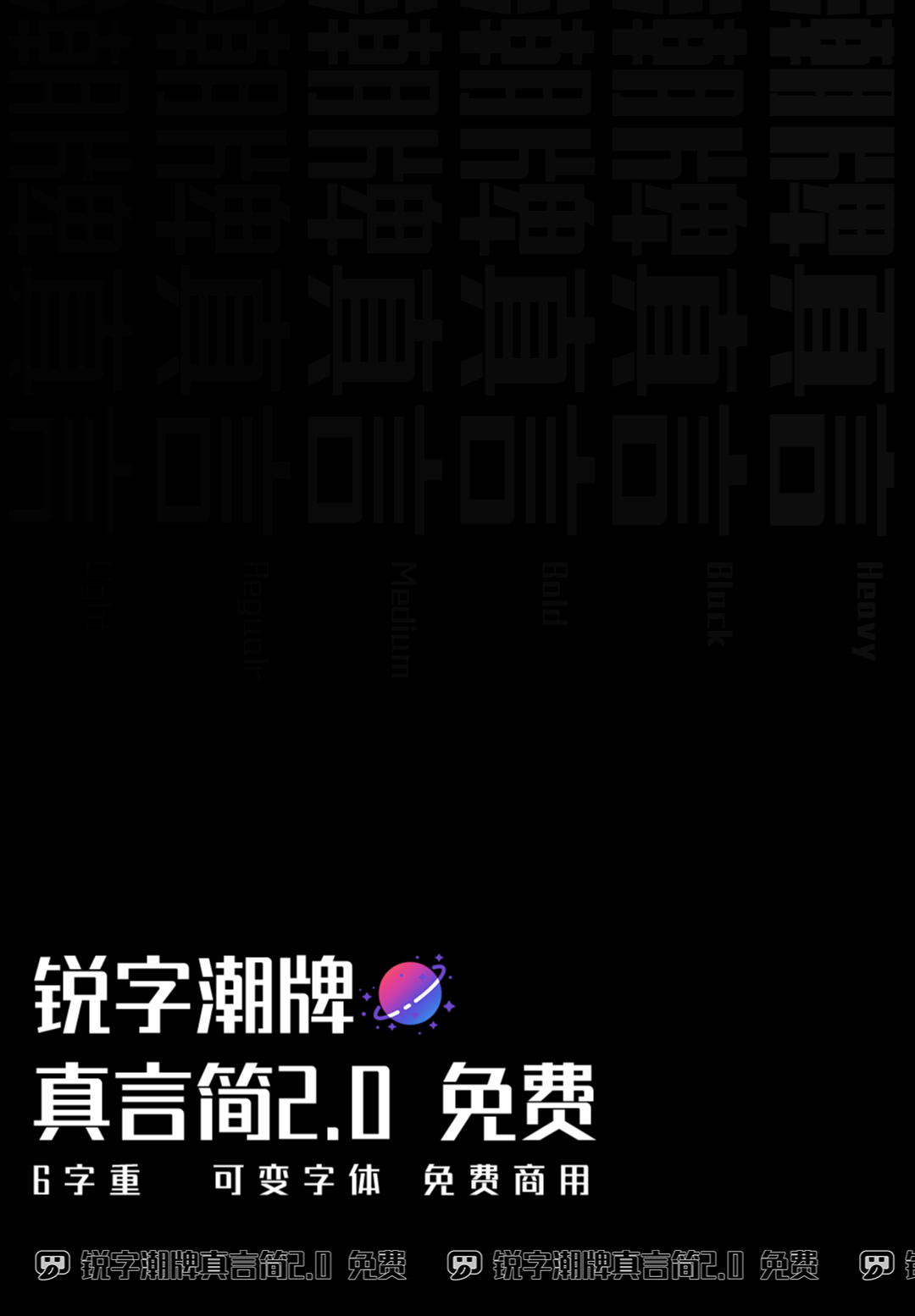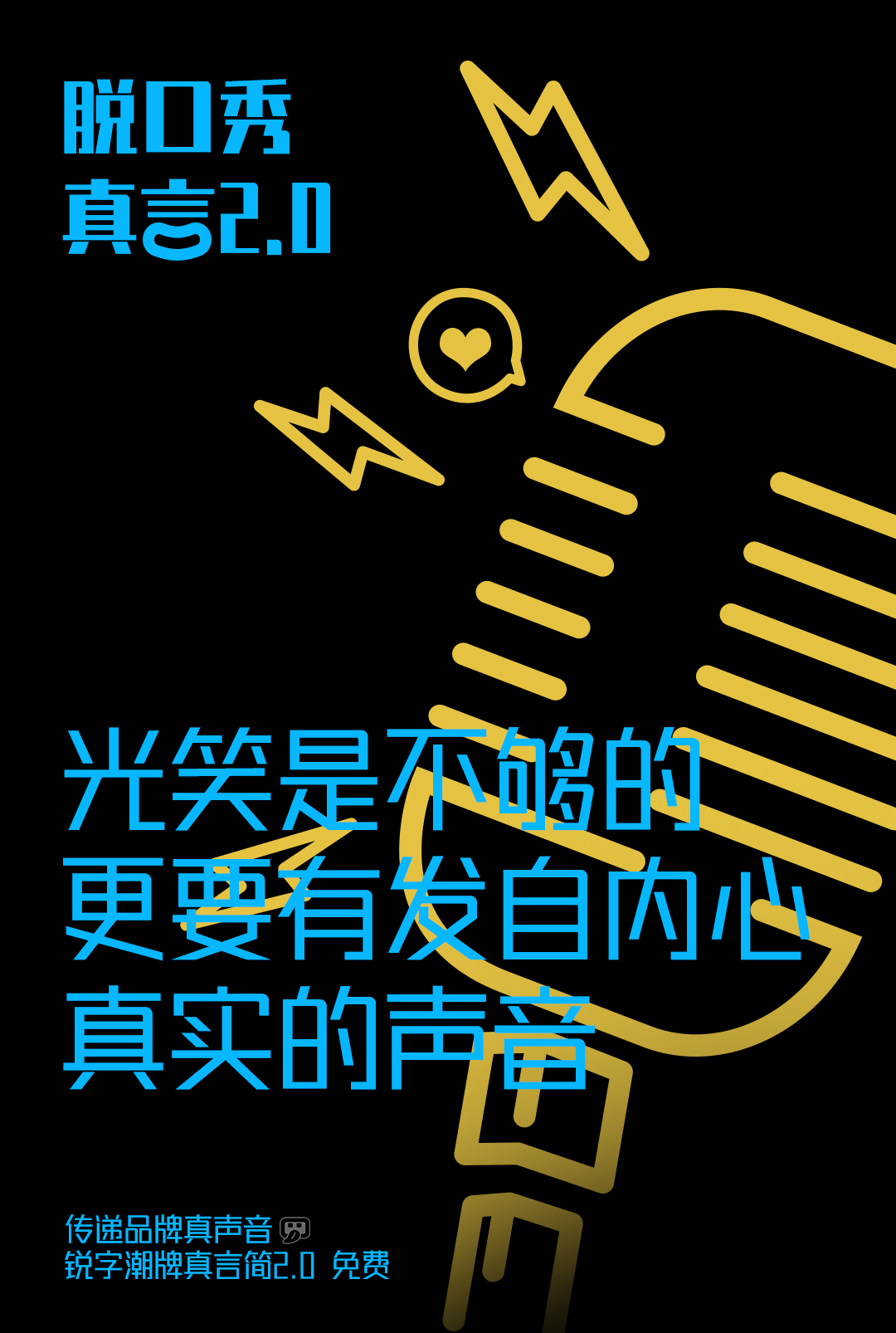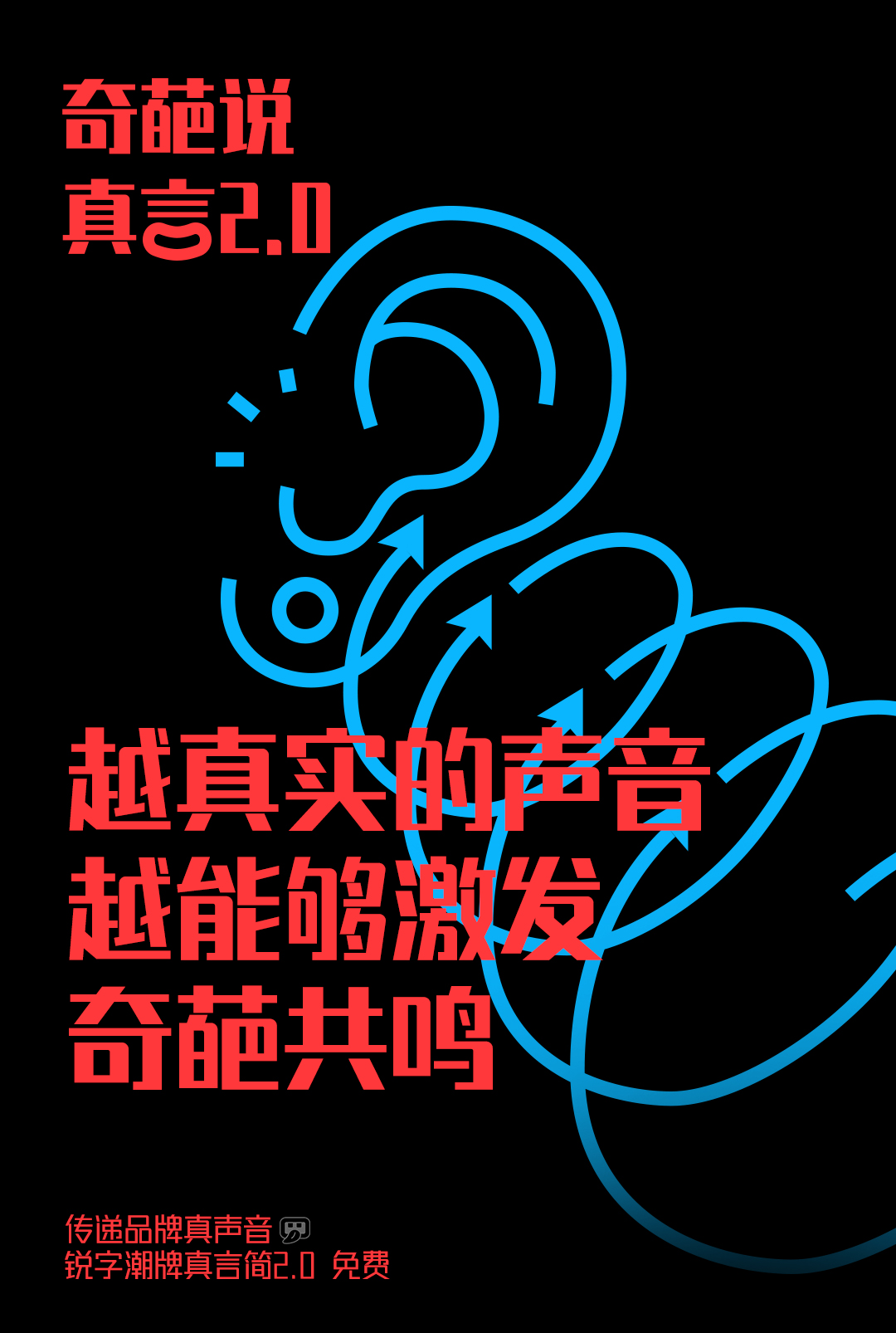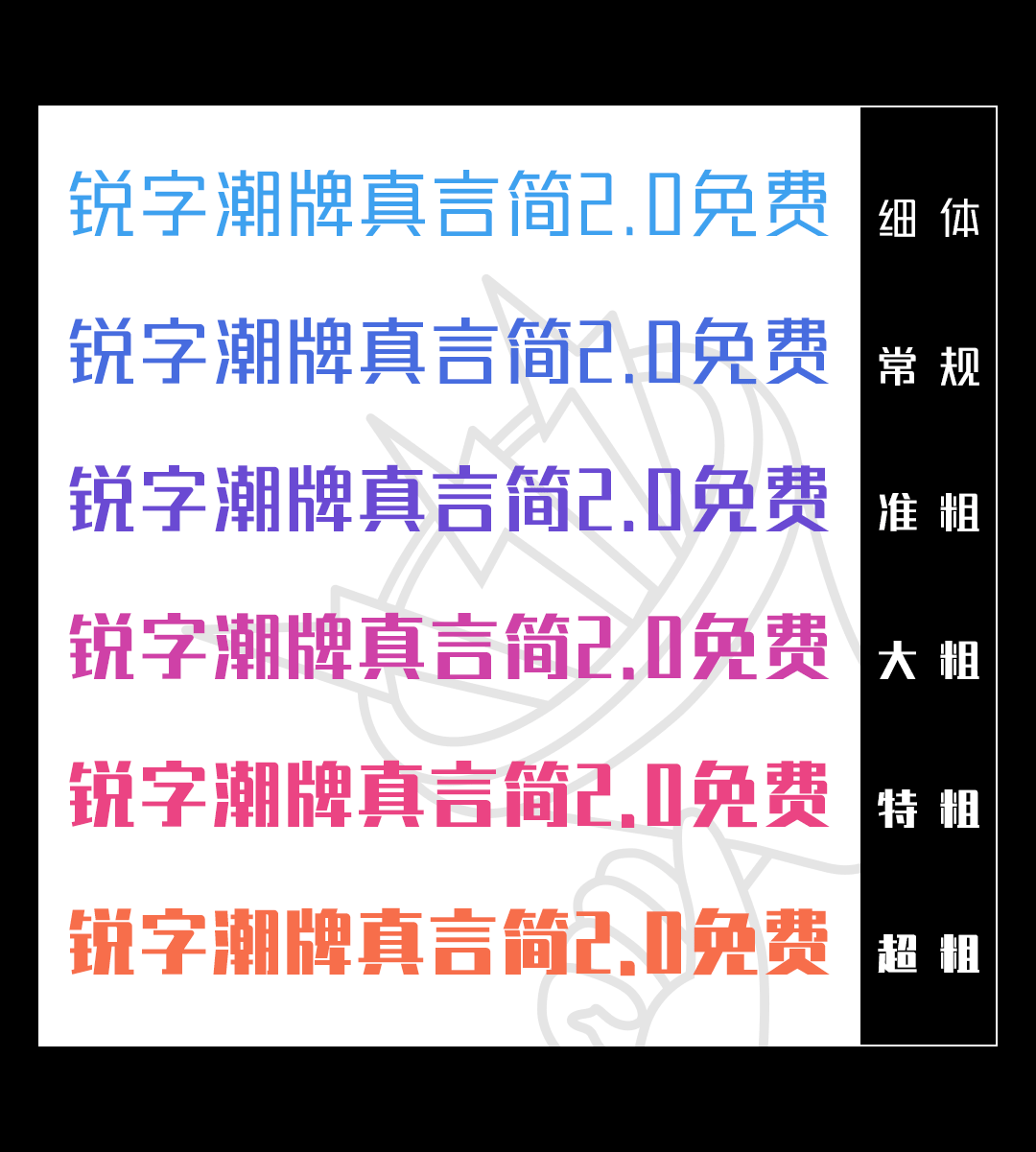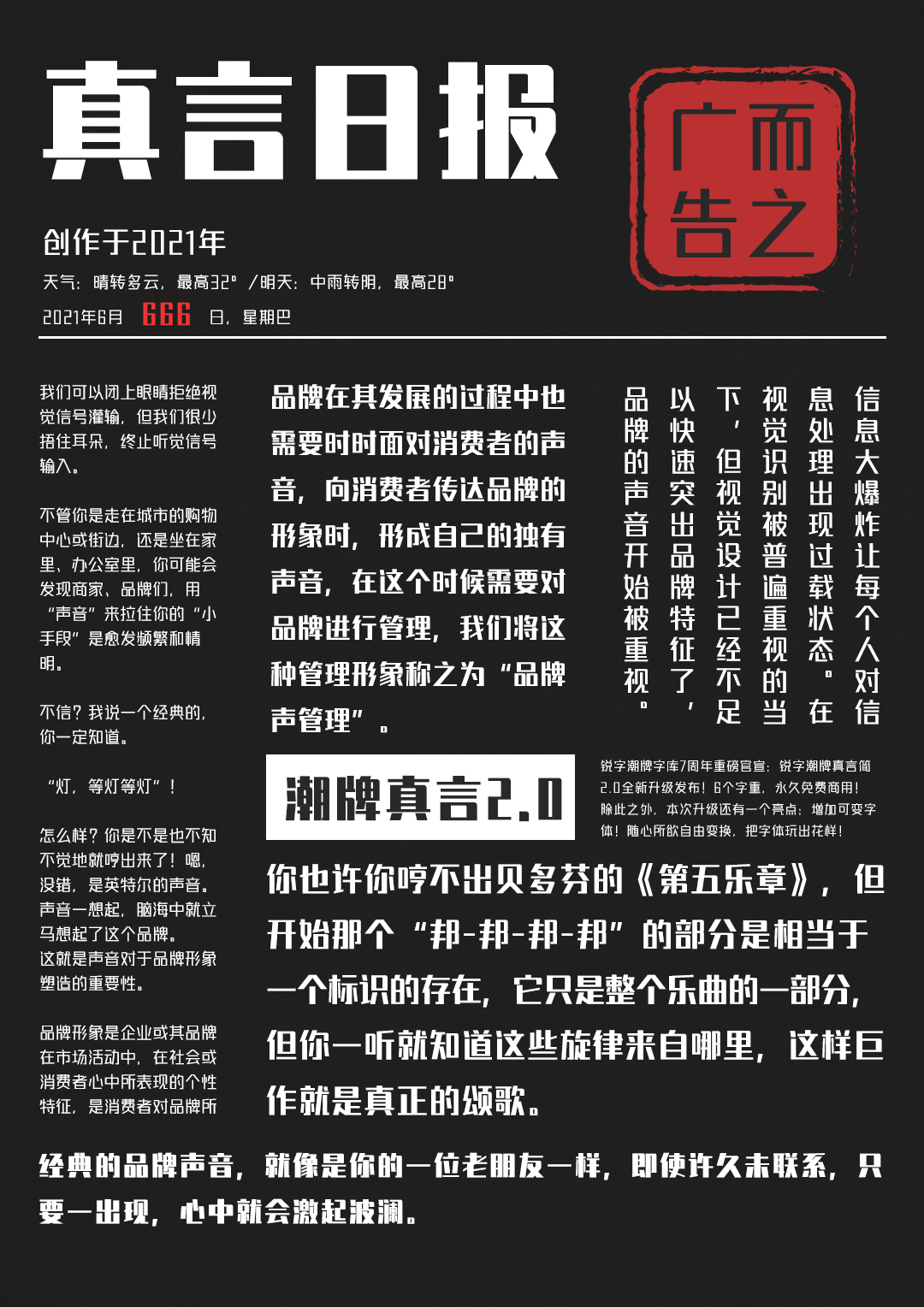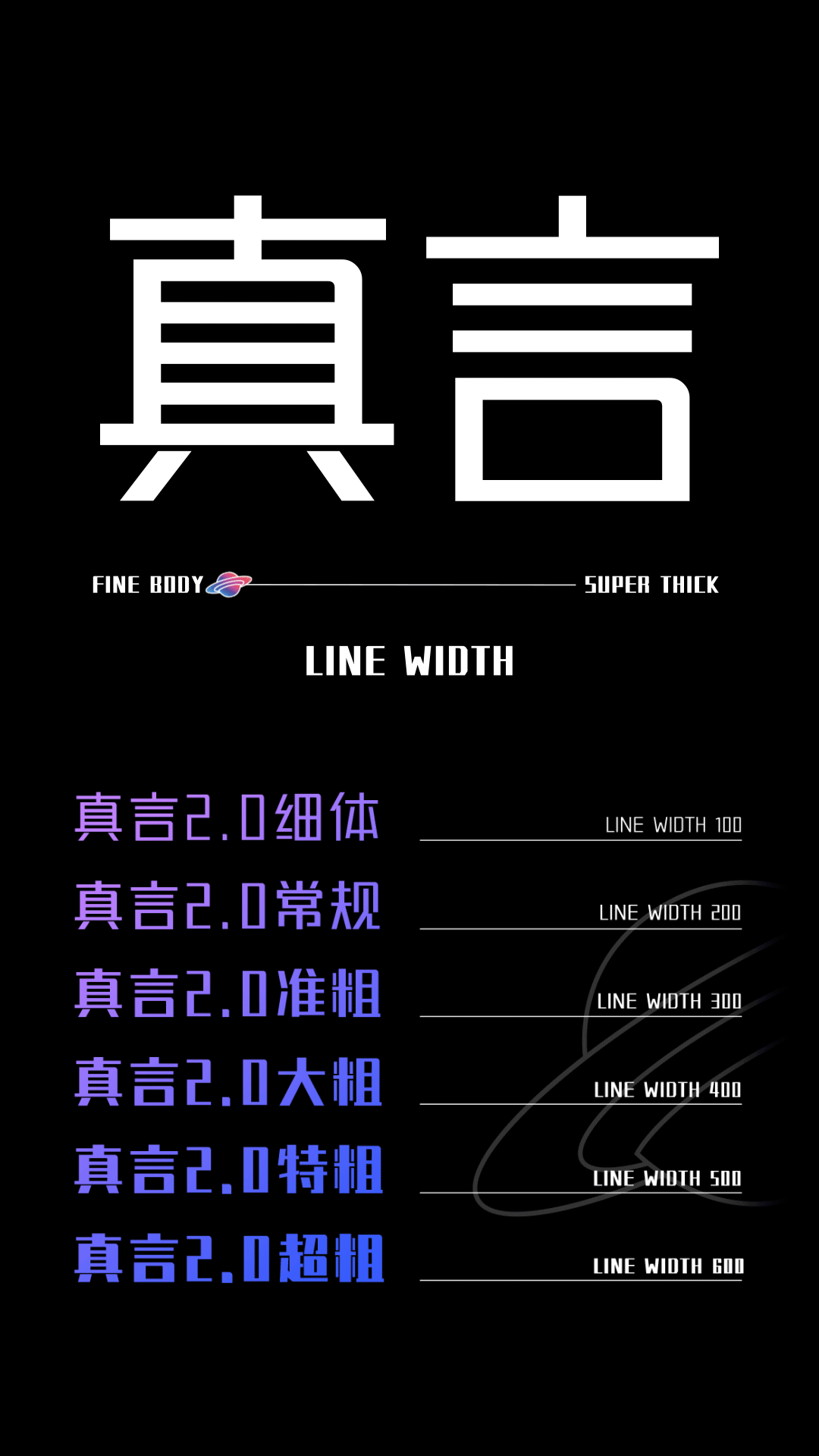
字潮牌字库成立7周年重磅官宣:锐字潮牌真言简2.0全新升级发布!免费商用!
本次升级调整字体结构;新增6个字重;增加17个繁体与生僻的常用字,共7672个字符。并支持可变字体!可随心所欲自由变换,把字体玩出花!现面向社会开放下载,
品牌真言,即品牌灵魂。锐字潮牌真言简2.0免费,在1.0版本基础上进行视觉升级,全方位展现品牌信息,更好地传递品牌真声音。
锐字潮牌真言简2.0在1.0版本基础上,衍生出5款系列化字体,共细体、常规、准粗、大粗、特粗、超粗6款字重,全面传播品牌真声音。
本次字体升级的另一个惊喜:新增可变字体技术!将含有字体粗细变化的字体文件,包含在单个字体文件中,从而实现随意切换,让字体呈现出不同的形态。
安装可变字体文件后,可以通过滑动调节字体的粗细,在这种自由的形态下,设计师可以按照设计需求、喜好来控制字体的使用范围,让字体具有无限延伸的可能性。